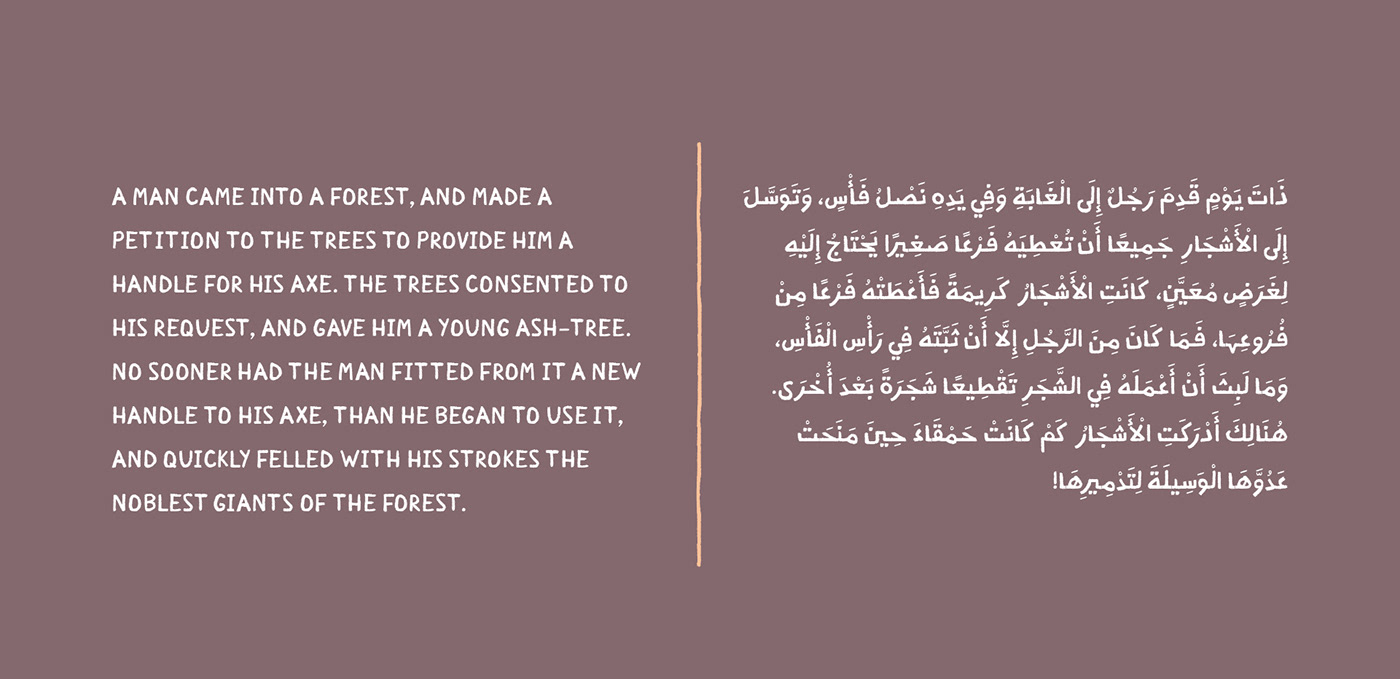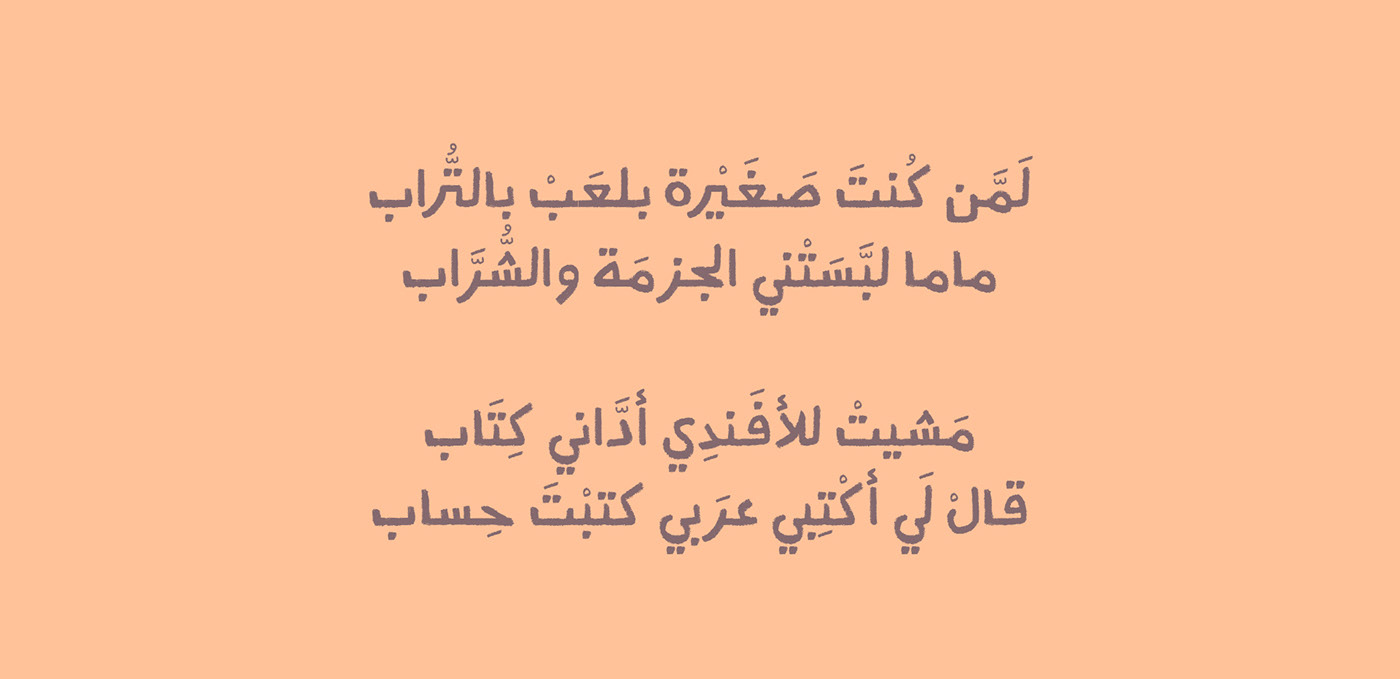
خط طبشور هو خط يدويّ لطيف مرسوم بأقلام طبشوريّة
Tabshoor is a cute typeface, hand-drawn with a crayon
تحتوي على الأحرف العربية واللاتينية البسيطة، والأرقام وعلامات الترقيم والرموز
Contains Arabic & Simple Latin characters, numerals, symbols and punctuation
تحتوي على الأحرف العربية والفارسية واللاتينية، والأحرف المركبة، والأرقام وعلامات الترقيم والرموز
Contains Arabic, Persian & Latin characters, Arabic & Persian ligatures, numerals, symbols and punctuation